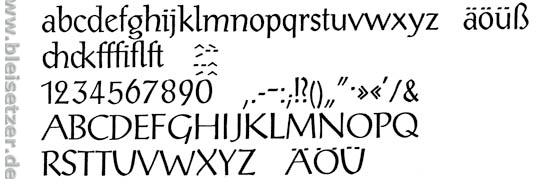
Schrift aus altem Zeugnis
weiss jemand, um was für eine Schrift es sich hier handelt?
stammt wohl aus einem ca. 40 Jahre alten Zeugnis.
ich würde sagen, das hat jemand von hand geschrieben, es gibt bestimmt schriften die den charakter haben aber das wird georg (bleisetzer) besser wissen als ich, ich müsste es suchen und das kann ich gerade nicht.
hm, ja, das hatte ich auch schon vermutet. Whatthefont und Identifont gaben auch nichts her.
Wäre super, wenn jemand mir evtl. ein, zwei ähnliche Schriften nennen könnte.
Mir sieht das mit den ch-Ligaturen nicht ganz so "gezeichnet" aus. Und genau wegen dieser Ligaturen sollte wenn, dann am ehesten Georg, der Bleisetzer wissen, was es ist ...
Wenn der Georg grad keine Zeit hat, dann werfe ich mal die Post Antiqua halbfett in die Runde.
Ich glaub zwar auch dass das handgeschrieben wurde (die 3 e's sehen mir nicht ganz ident aus) aber vielleicht war die PostAntiqua die Durchpausvorlage …
Ich glaube auch nicht, daß das ein Bleisatz-Font ist.
Und die Post Antiqua wurde für solche Urkunden und Zeugnisse sehr gern genommen, eine gute Empfehlung.
Übrigens gibt es diese Schrift auch als reinen Versalschnitt. Die läuft etwas breiter und kräftiger als die Versalien der Post-Antiqua.
Vergleiche
Post-Antiqua:
Post-Versal: